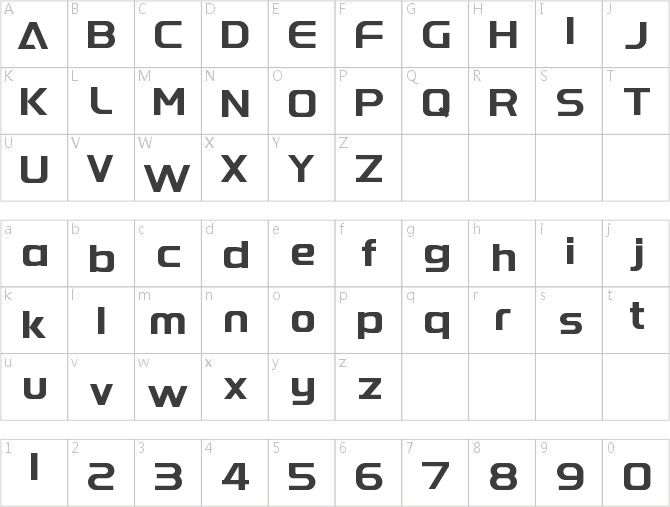
字体名称: ZuoZi-l
ZuoZi-logo
ZuoZi-logo字体下载左字西文LOGO体
ZuoZi-logo字体左字西文LOGO体字库是一款让人赏心悦目、百看不厌的英文字体,适合各类广告和产品包装设计应用,字体大小0.01MB,格式为ttf字体,上传用户是Amanda白卉,作者/版权方为左字字库